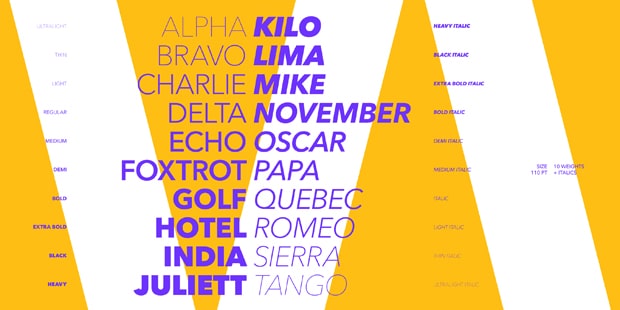
Monotype erweitert Avenir-Schriftfamilie
Die Schriftdesigner des Monotype Studio stellen die Erweiterung der Avenir-Schriftfamilie vor: zwei neue Strichstärken und fünf weiteren Schreibsysteme für über 150 Sprachen kommen hinzu.
Mit Avenir Next World präsentiert Monotype nach eigenen Angaben eine globale Schriftfamilie, die mehr als 150 Sprachen und insgesamt acht Schreib- bzw. Zeichensysteme unterstützt, darunter Kyrillisch, Griechisch, Hebräisch, Arabisch, Georgisch, Armenisch und Thai. Die Bandbreite der Strichstärken – von Ultra Light bis Heavy – wurde von acht auf zehn erweitert und im kräftigen Bereich mit den beiden neuen Schnitten Avenir Next World Extra Bold und Black feiner abgestimmt.
Die erweiterte Familie soll globalen Marken neue typografische Inszenierungsmöglichkeiten im Genre der Geometrischen Sans bieten.
Kurze Geschichte der Avenir
Avenir, 1988 entworfen von Adrian Frutiger, zählt zu den berühmtesten Schriften der Welt und wurde mit der Absicht entwickelt, eine lineare Sans in der Tradition von Erbar und Futura zu entwerfen und gleichzeitig die Erfahrungen und stilistischen Design-Erkenntnisse des späten zwanzigsten Jahrhunderts einfließen zu lassen. Aufgrund der rasanten Entwicklung in der digitalen Satztechnik, setzte sich nur 15 Jahre nach der Premiere der Schrift Akira Kobayashi, Creative Type Director bei Monotype mit Adrian Frutiger zusammen, um die stark erweiterte Avenir Next zu entwickeln. Neuerungen gegenüber dem Original waren: mehr Strichstärken, Condensed-Schnitte, Kapitälchen und der Wegfall des Nummernsystems für die Schnittnamen. Damit war die Schriftfamilie sowohl für die Print- als auch die Bildschirm-Widergabe geeignet. Heute, fast 20 Jahr später, streben mehr Marken als je zuvor die Globalisierung an, wodurch eine konsistente visuelle Identität weiter an Bedeutung gewinnt.
Kobayashis Erfahrung mit der Entwicklung und dem Ausbau von Frutiger-Designs floss nun in die aktuelle Ergänzung von Avenir Next mit neuen Sprachen ein; zudem koordinierte Kobayashi weltweit anerkannte Kolleginnen und Kollegen um die Avenir Next auf das nächste Level zu heben, darunter Yanek Iontef, Nadine Chahine, Toshi Omagari, Akaki Razmadze, Elena Papassissa, Anuthin Wongsunkakon und die Font-Ingenieure des Monotype Studio.
Die Entwicklung von Avenir Next World basiert auf der Expertise all dieser Type-Designer.